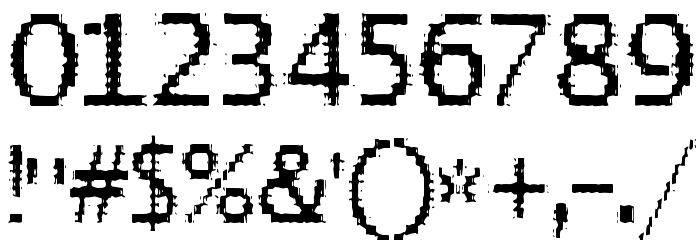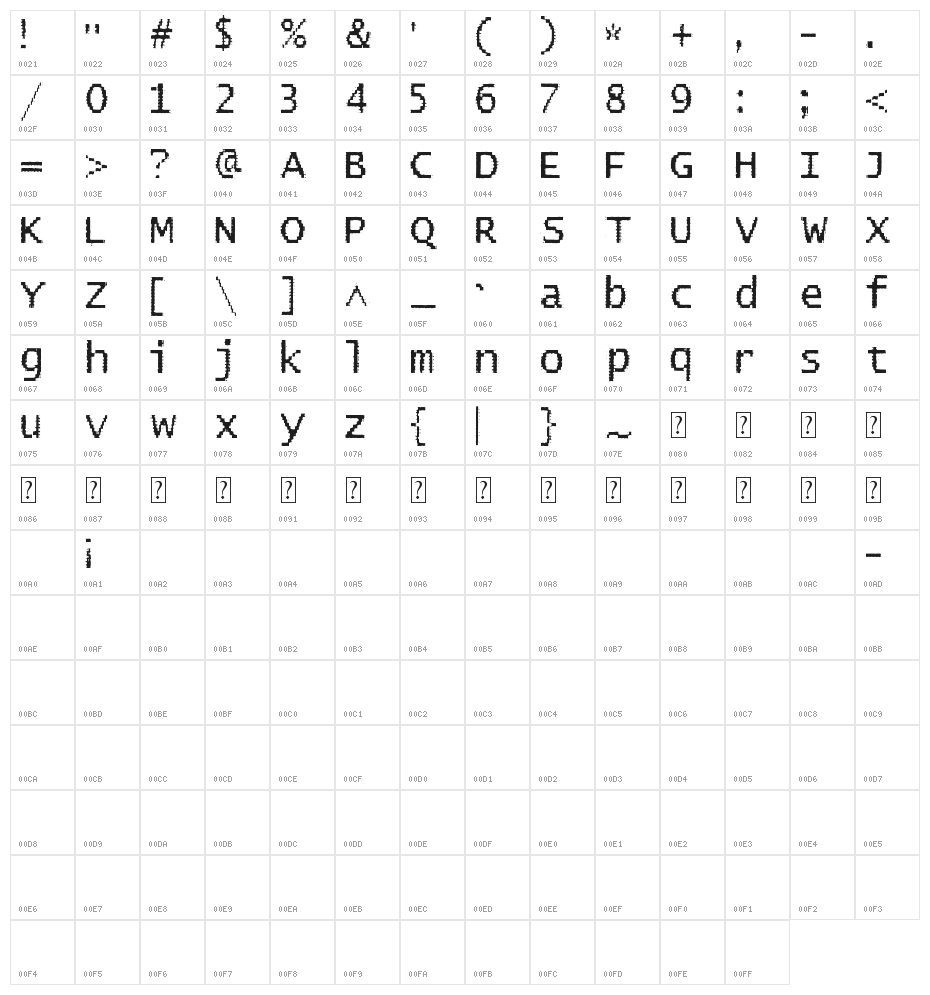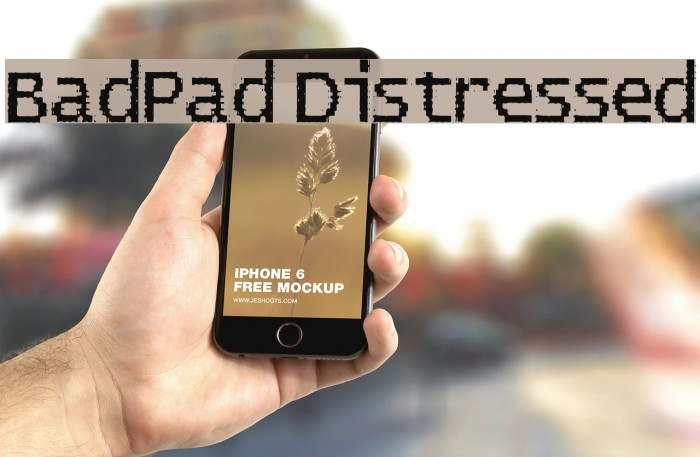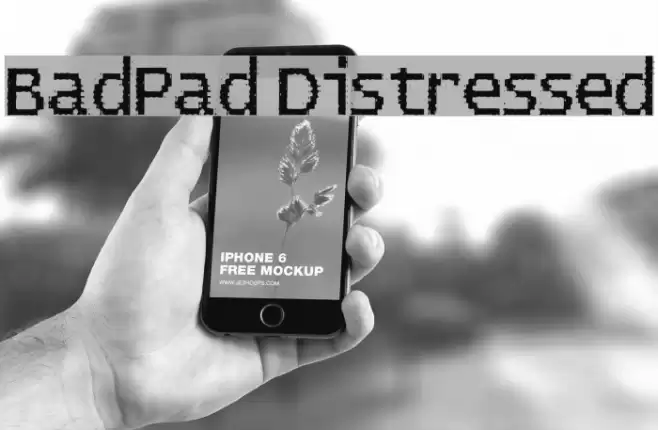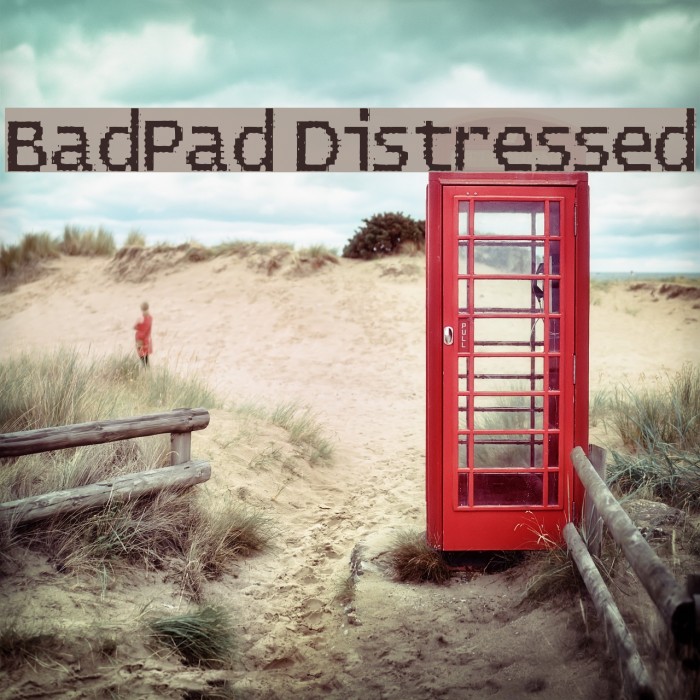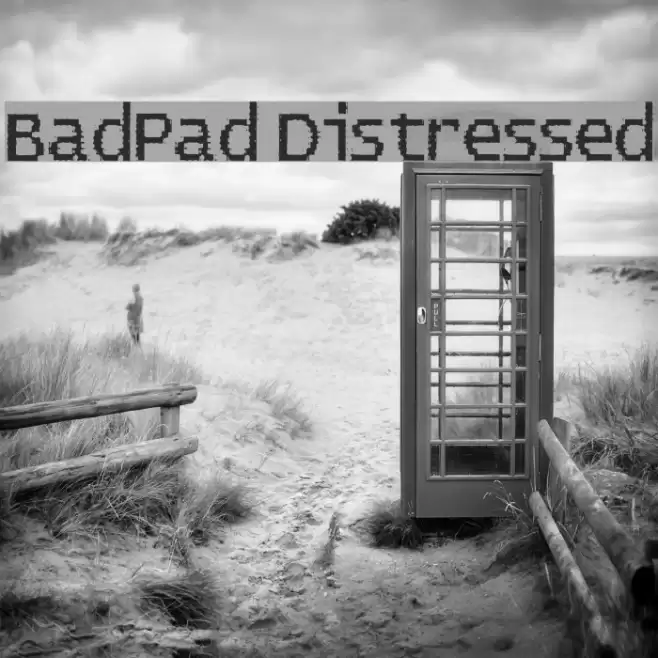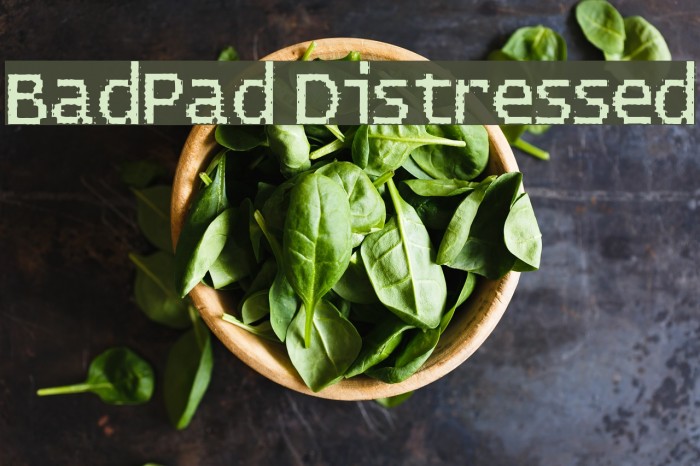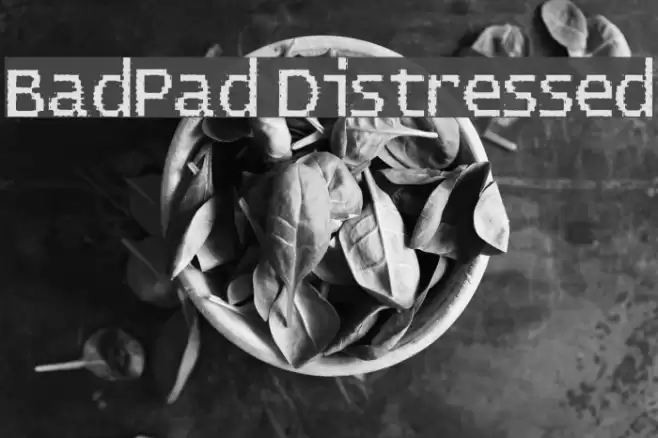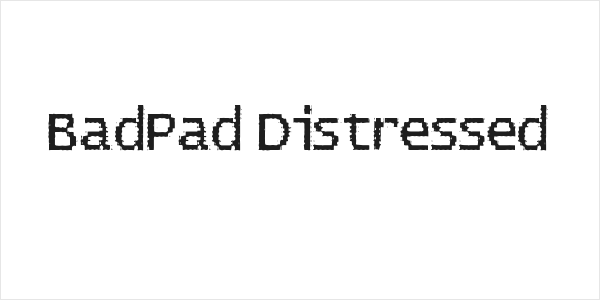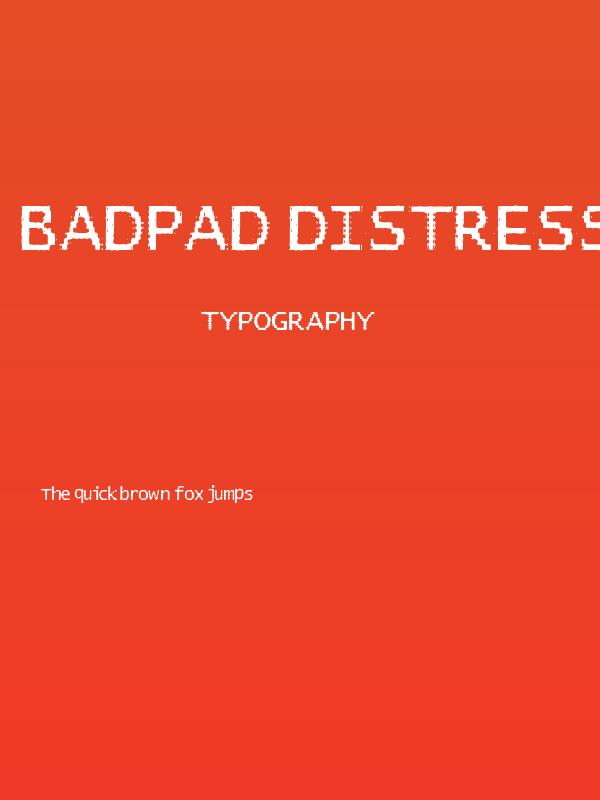
BadPad Distressed Font
✎ Distorted Eroded
| おすすめプロジェクト | Ideal for vintage posters, retro-themed designs, branding for rustic or industrial products, and any project needing a gritty, aged look. |